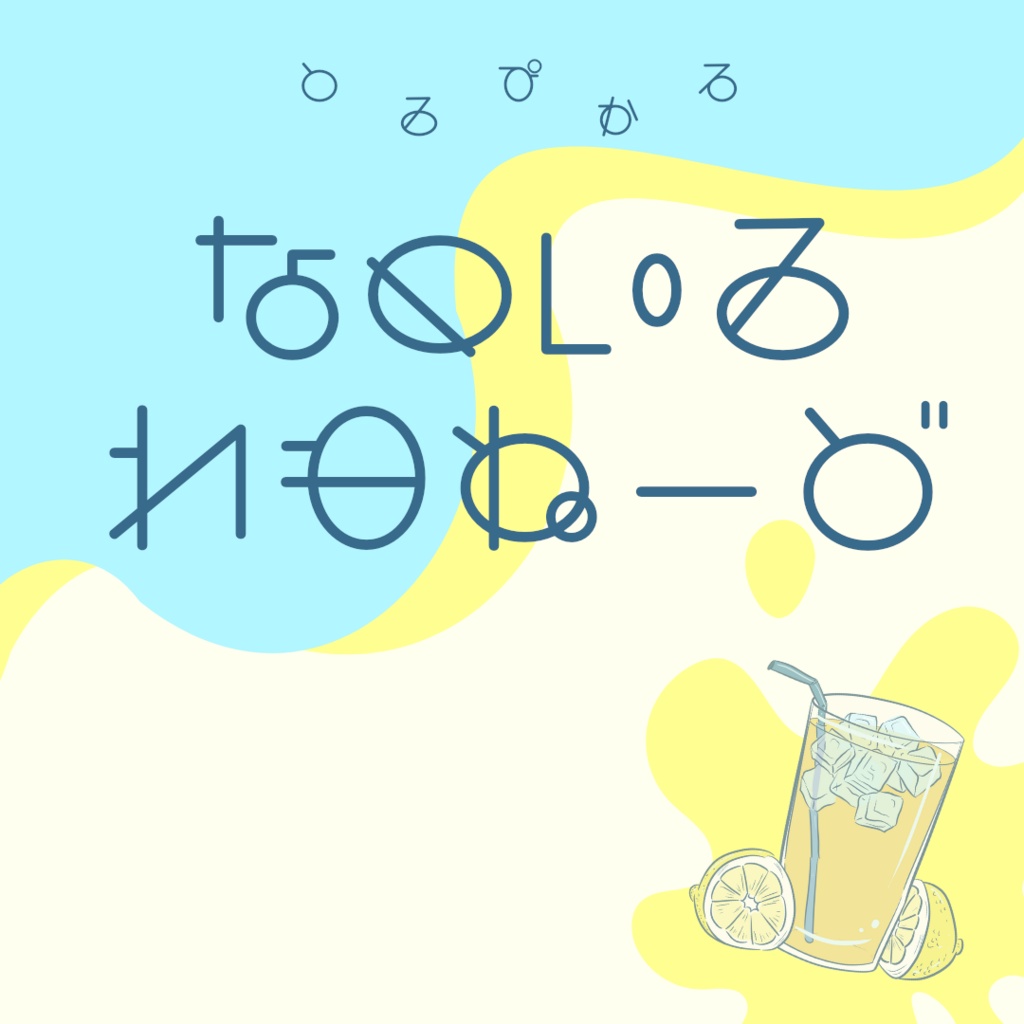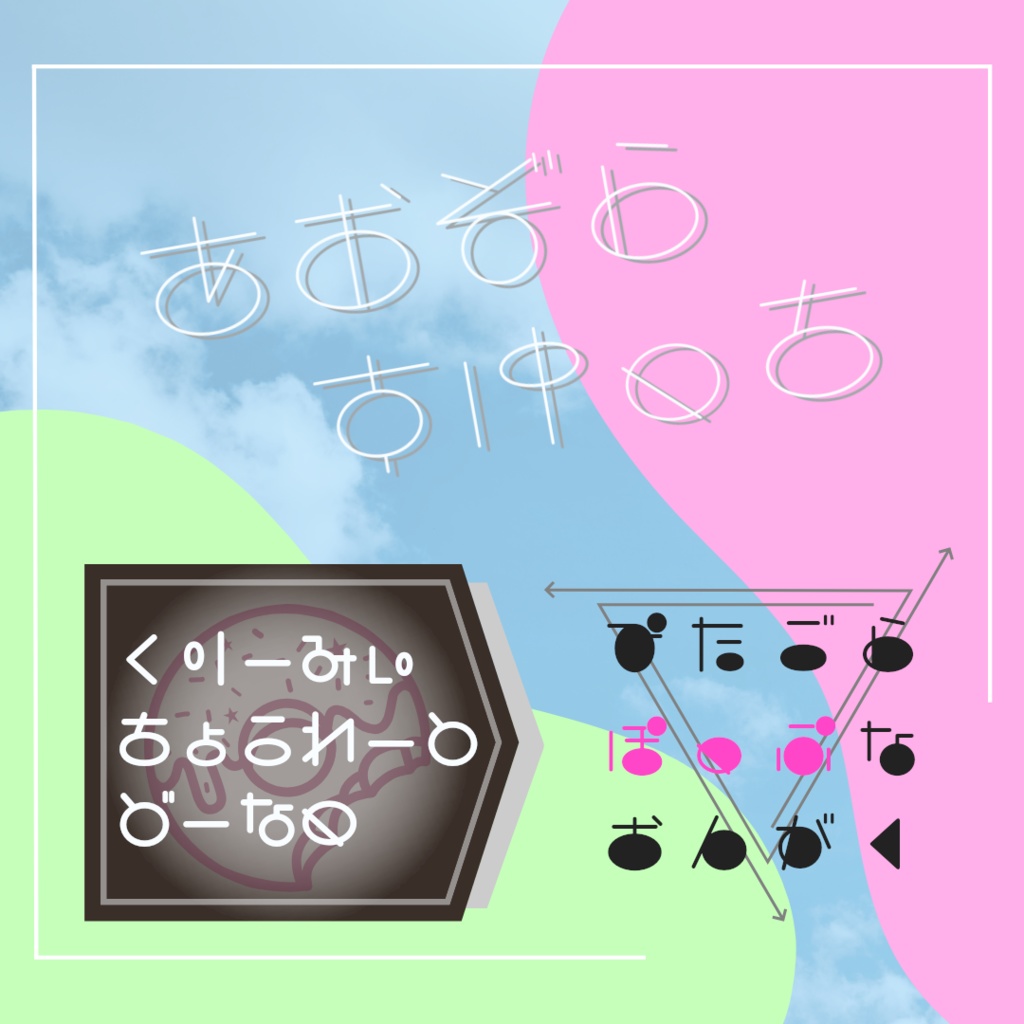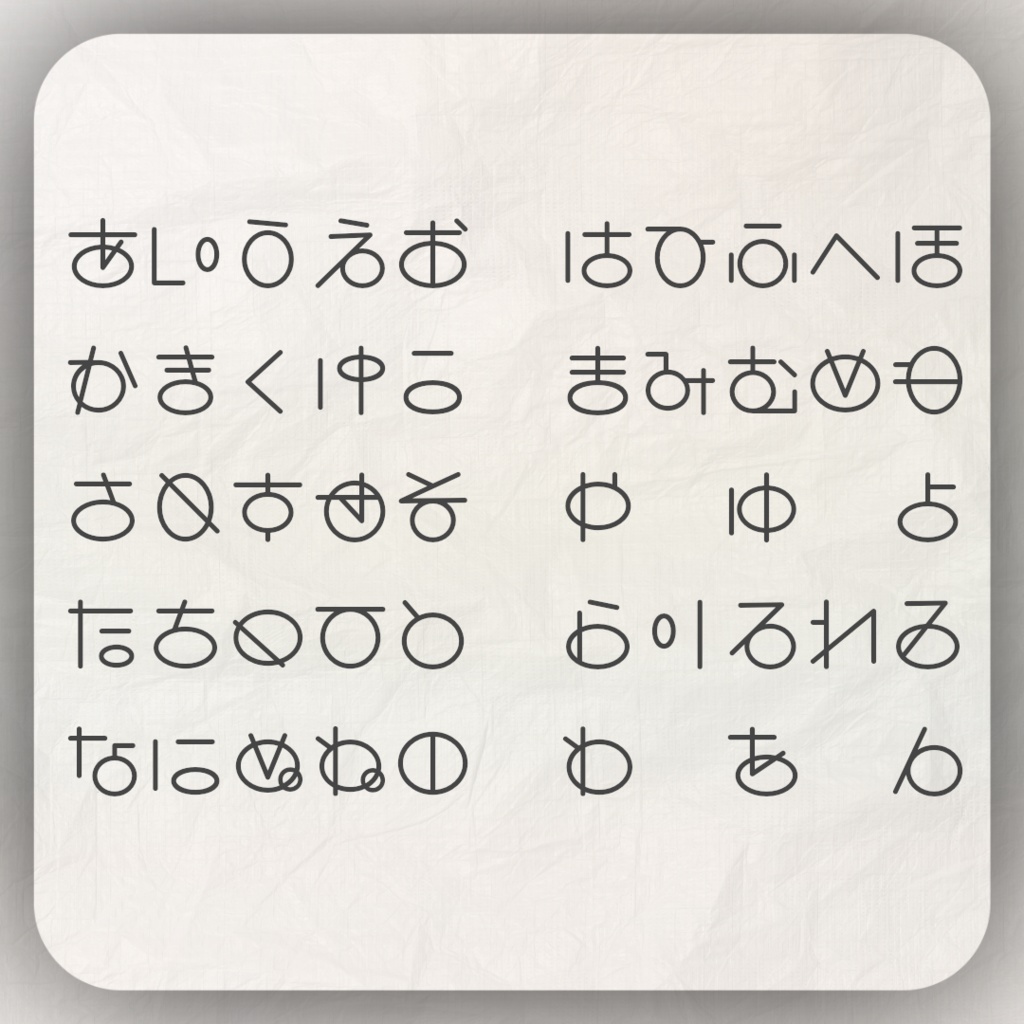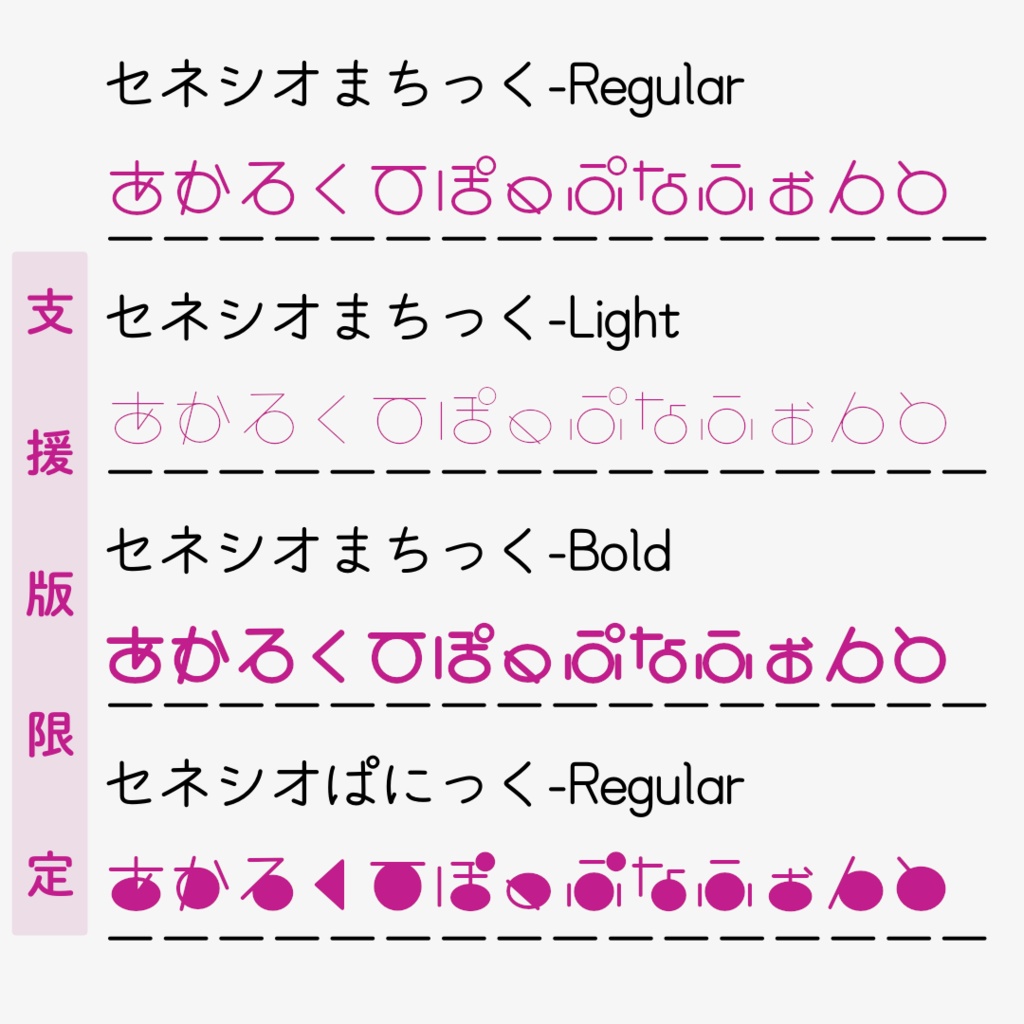
【フリーフォント】セネシオまちっく
直線と円のみを組み合わせたポップなフォント「セネシオまちっく」。 読めなさそうで読めない…かと思いきやギリギリ読めるかも?くらいのラインを目指した、決して読みやすいとは言えないフリーフォントです。 収録文字はひらがなのみ。可愛くタイトルを彩ったり、暗号チックに使ってみたり、楽しみ方は無限大! 今回は支援版におまけを付けてみました。 「セネシオまちっく」の別ウェイト(Light /Bold)と、円を塗りつぶした「セネシオぱにっく」を収録しております。 利用報告は不要ですが、BOOTHのメッセージやX(Twitter)のDM等でご利用やご感想についてお知らせいただけますと、大変励みになります!
収録文字